¿Cómo fue auge histórico de las tipografías sans-serif?
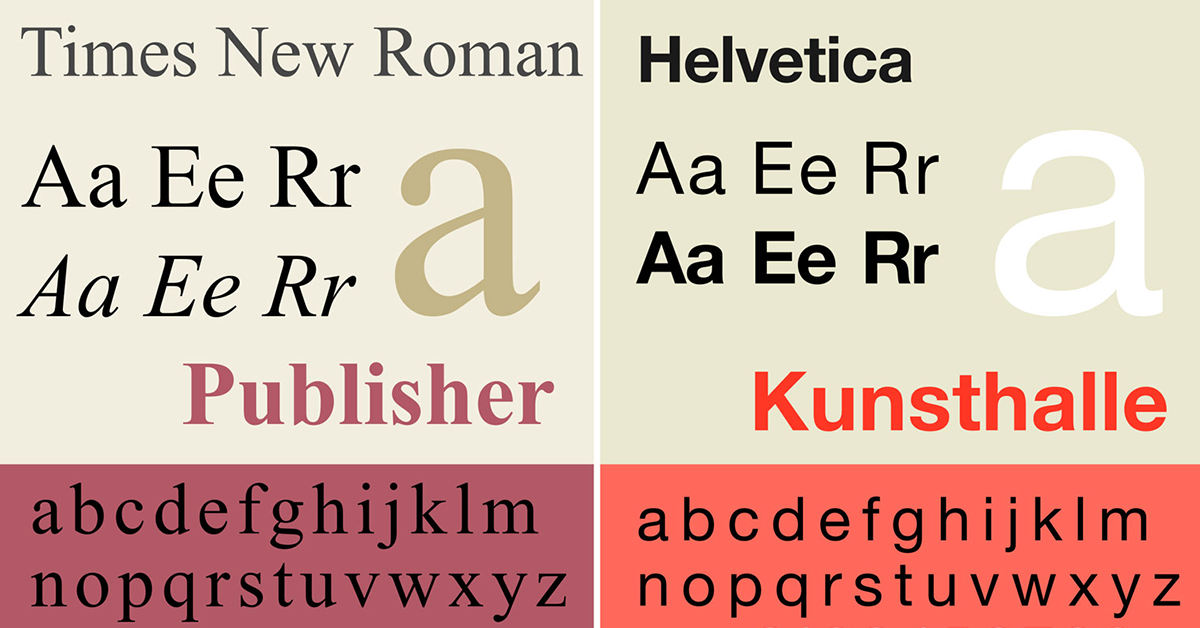
Aunque al inicio no gozaron de gran aceptación, las tipografías de palo seco han logrado hacerse con la hegemonía.
Aunque hoy en día, prácticamente en cualquier lugar en el que pongamos nuestra mirada, encontraremos tipografías sans-serif, esto no fue así hasta finales del siglo XX. El ensayo-documental How sans-serif fonts took over the world (que puedes ver al final de este post), de Michael Thomas, hace un breve repaso por los hitos que auparon a las tipografías de palo seco al éxito y aceptación del que gozan en la actualidad.
No fue hasta el siglo XX cuando comenzó a tomarse enserio a las tipografías sin serifas, de hecho estaban consideradas tipografías poco serias y ninguna editorial quería incluirlas en sus publicaciones. En 1928 Jan Tschichold publicó The new typography, un libro que defendía el modernismo, exponía el incremento de una población acomodada y educada y hablaba del auge de la publicidad. Un libro que, aunque terminó convirtiéndose en una especie de biblia para tipógrafos, en aquel momento gozó de escasa aceptación.
Con la llegada de Hitler al poder en 1933, se conminó a todos los diseñadores gráficos a registrarse en el Ministerio de Cultura. A los pocos días la policía encontró varios pósteres comunistas en la casa de Jan Tschichold, que este atesoraba no por su significado político, sino por su valor tipográfico. Él y su mujer fueron arrestados, pero consiguieron escapar a Suiza, donde se unieron a un grupo de tipógrafos entre los que se encontraba Paul Renner, quien años más tarde diseñaría la tipografía Futura. El avance de los nazis y la necesidad de estos tipógrafos de buscar asilo en países como Estados Unidos y Reino Unido, trabajando en fundiciones tipográficas, editoriales, agencias de publicidad, etc. tuvo como consecuencia la expansión del uso de las tipografías sans-serif, convirtiéndose en la elección tipográfica de todo tipo de empresas, gobiernos y corporaciones.
Como consecuencia de todo esto, Michael Thomas hace una comparativa entre el número de titulares en el que se usaron tipografías de palo seco en el año 1895 (5%) y cuántos lo hicieron en 1955 (54%), observando un crecimiento abrumador que muestra el auge de las tipografías con serifa en detrimento de las sans-serif.
El vídeo-ensayo How sans-serif fonts took over the world (en inglés) explica el éxito de las tipografías sin serifa y nos ayuda a comprender cómo han llegado a convertirse en el tipo de fuentes más usado en la actualidad.